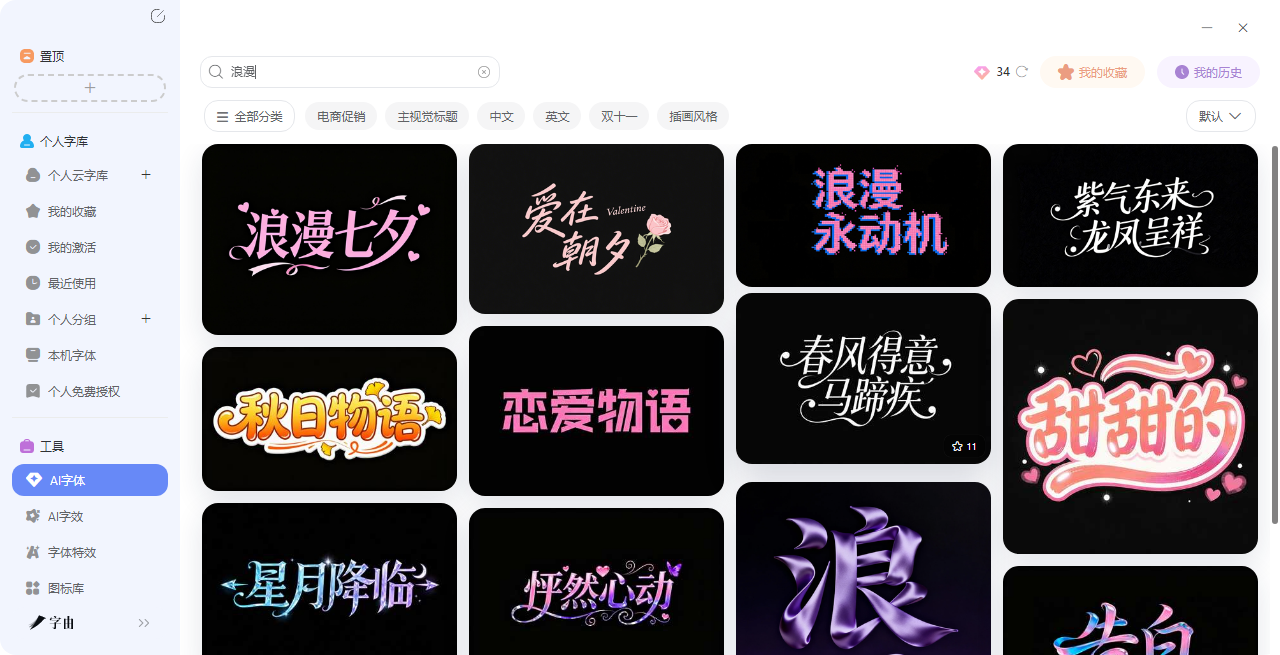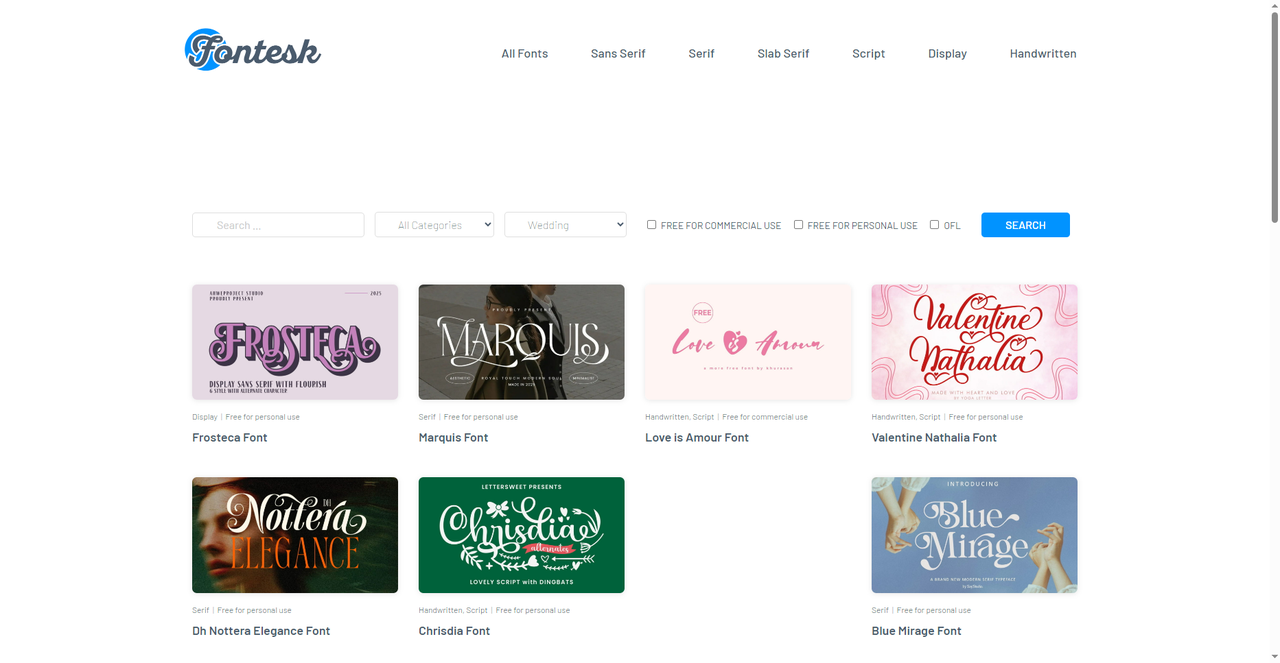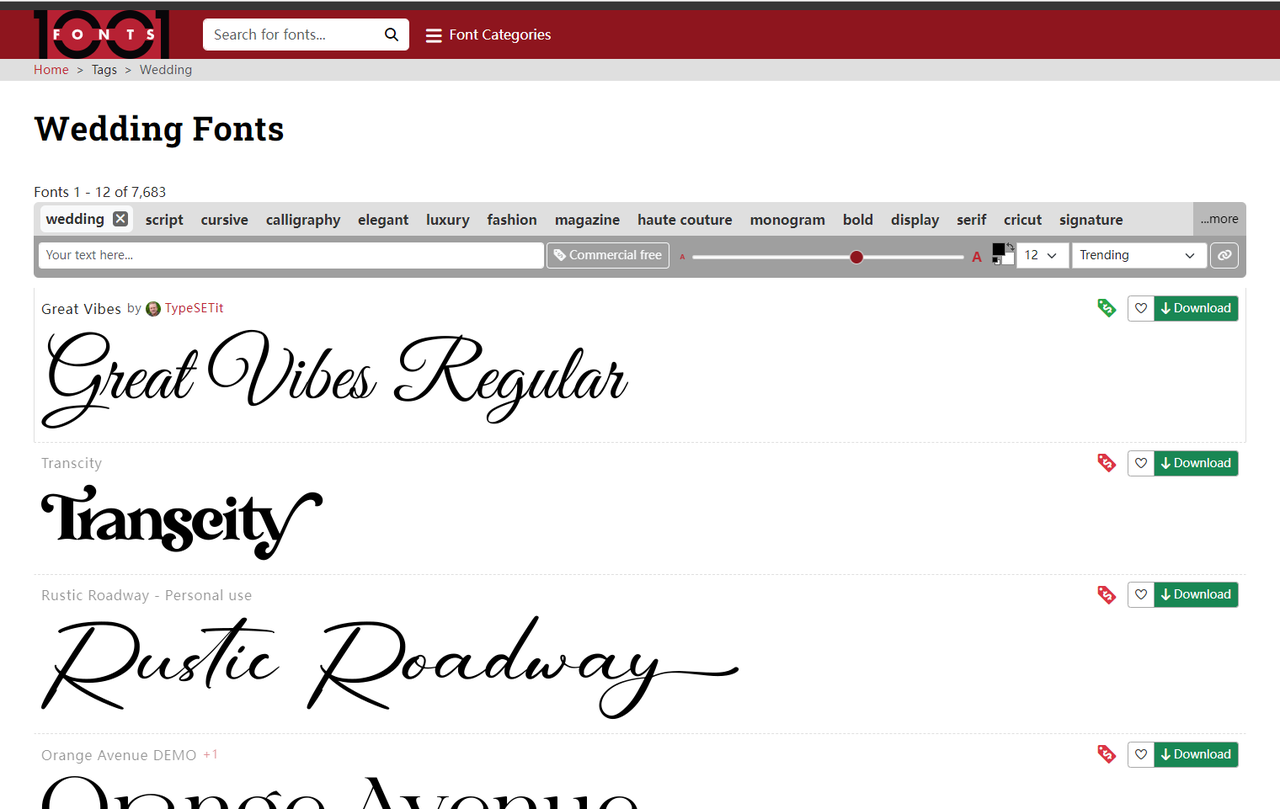
不会设计也能做请柬字?试试这几个婚礼请柬字体生成工具
婚礼请柬是现在备婚必不可少的一个环节,虽然说请柬可以是电子版也可以有现实的纸质版,但是无一例外都逃不过需要合适的字体。问题是,市面上的字体那么多,哪个才能适合自己婚礼风格的呢?自己设计吧,没那功底;花钱请人吧,预算又紧张。其实,现在有不少婚礼请柬字体生成工具,输入文字就能一键生成,根本不需要你会设计。在今天的文章里我会推荐4 个亲测好用的婚礼请柬字体生成工具,每个都能帮你快速搞定请柬上的字。需要的直接收藏!
备婚的时候,最纠结的事情之一就是请柬上的字。选太普通的怕没仪式感,选太花哨的又怕不够庄重,自己写吧字迹不好看,找人写吧又不知道去哪找。其实,字由的AI字体功能就是专门解决这个纠结的。你不需要会书法,也不需要懂设计,打开客户端,搜一下“婚礼”,就能看到一堆为请柬量身定做的模板。
接下来我会给大家介绍一下如何用字由的AI 字体来制作婚礼请柬字体!
第一步:进入AI字体页面后,在搜索框里输入“婚礼”“浪漫”“请柬”等关键词,系统会自动筛选出所有适合做请柬字的模板。你也可以直接点进“节日”“浪漫”等分类里慢慢翻,很多促销模板稍改文案就是极好的请柬字。
第二步:选一个喜欢的请柬模板,每个模板都有独特的设计。
• 优雅手写类:“浪漫”“誓言”这种,适合做主标题
• 温柔圆润类:“温柔”这种,适合做副标题
• 连笔浪漫类:“携手”这种,适合做封面字
• 简约稳重类:“余生”这种,适合做信息文字
• 英文花体类:“Wedding”“Love”这种,适合做英文标题
每个模板都有预览图,你可以先看效果再决定,点进去还能看到更多细节。选一个和你婚礼风格搭的,如果拿不准,可以多试几个。、
第三步:点击选中的模板,进入编辑页面。在输入框里填你想生成的请柬内容,比如“我们结婚啦”“余生请多指教”“见证我们的爱情”。注意:最好和模板的字数保持一致,但可能会有些偏差,所以建议按模板字数来。
第四步:确认文案后,点“立即生成”,等20-30秒左右就能拿到图。生成后可以预览效果,不满意就换其他模板再试,或者微调文案重新生成。每天有免费算力点,日常试用完全够用,下载时有两个选项:带背景的可以直接用,透明背景的更方便后期排版。直接保存PNG格式,就能拖进PS、Canva或者请柬制作软件里继续调整。
而且,除了AI生成,字由本身也有大量适合做婚礼请柬字体的免费商用字体,比如说:
• 字由芳华体:温柔手写,适合做请柬的主标题
• 字由文艺黑:大气稳重,适合做新人名字的排版
• 江西拙楷:朴拙手写,适合做中式婚礼请柬
• 优设标题黑:方正有力,适合做时间地点的标注
你可以在AI字体里直接调用这些字体,也可以先用字体库选好,再套用请柬模板,组合出更多可能。如果对某个模板的效果特别喜欢,还能保存下来,下次直接调用,不用重新设置。
2、Fontesh
Fontesh 是一个专门收集免费字体的平台,它的“Wedding”分类下收录了大量适合请柬的字体。从截图看,这些字体风格多样,每款都标注了授权类型:
• Frostecafont:Display风格,免费个人使用。字体纤细优雅,适合做请柬的正文或小标题。
• Marquis font:Serif风格,免费个人使用。经典衬线体,稳重高级,适合做新人名字的排版。
• Valentine Nathalia font:Handwritten, Script风格,免费个人使用。花体字,有装饰性卷曲,适合做英文请柬。
3、Fontspace
在Fontspace 里,它的“Wedding Invitation Fonts”分类收录了5938 款字体,相关风格标签包括:Cool、Calligraphy、Cursive、Fancy、Lettering、Script、Handwriting、Cute、Modern、Serial……几乎覆盖了所有请柬可能用到的风格。每款字体都有下载次数和用户评分,可以帮助你挑选,但是下载的时候要注意区分个人使用和免费商用。
4、1001 Free Fonts
1001 Free Fonts 是一个老牌字体网站,它的“Wedding Fonts”分类收录了7683 款字体。主页上推荐的这前几款特别实用:
• Great Vibes Regular:经典手写体,优雅流畅,适合做请柬的主标题。
• Transcity:现代感强的字体,适合做现代风婚礼的标题。
• Rustic Roadway:乡村复古风,标注“Personal use”,适合做田园风婚礼请柬。
• Orange Avenue DEMO:展示字体,适合做装饰性标题。